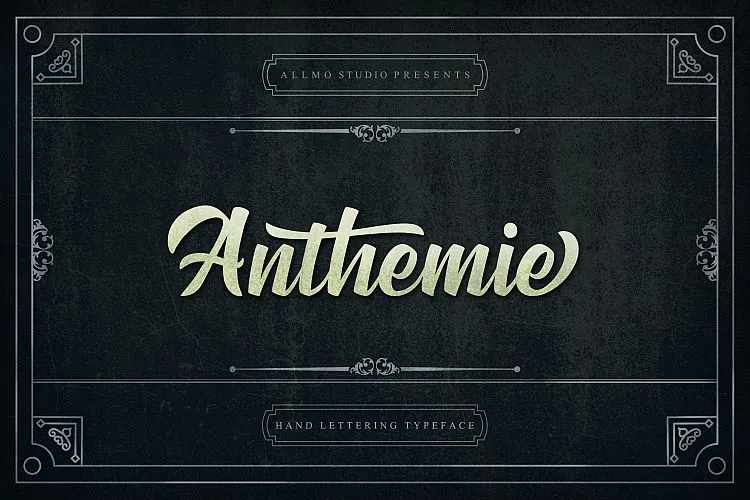
Anthemie Script Font é uma delicada tipografia script com personalidade que combina estilos serifado e sans-serif para criar mensagens atraentes. Seu design fluido, ideal para usar de diversas maneiras, tem uma vasta variedade de alternativas para atender a múltiplas necessidades de projetos. Inspirada em um estilo moderno vintage, Anthemie Script é perfeito para sua identidade visual vintage, como logomarcas, selos, roupas ou qualquer outro design que exija uma letra única e sofisticada. Além disso, veio com letras maiúsculas e minúsculas frescas, números, ligaduras e alternativas estilizadas para se adaptar ao seu projeto de forma harmoniosa. Este é um excelente exemplo de como a Anthemie Script pode revolucionar seus projetos gráficos.